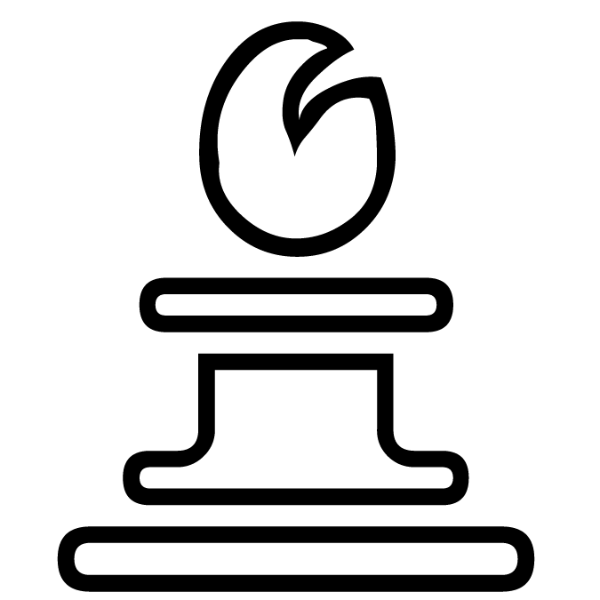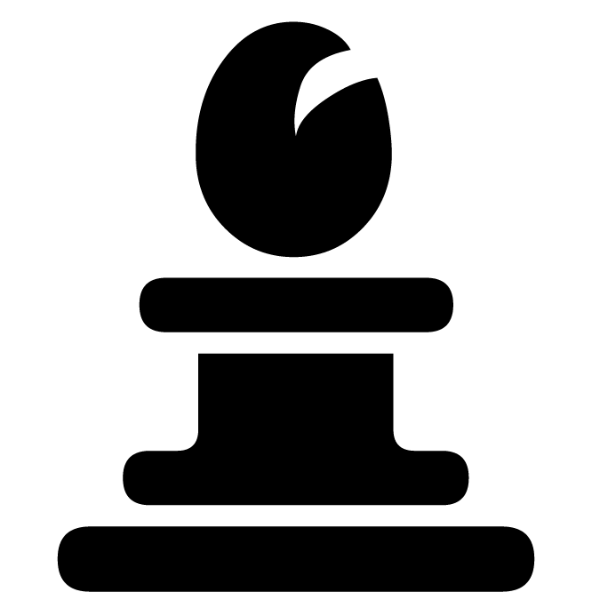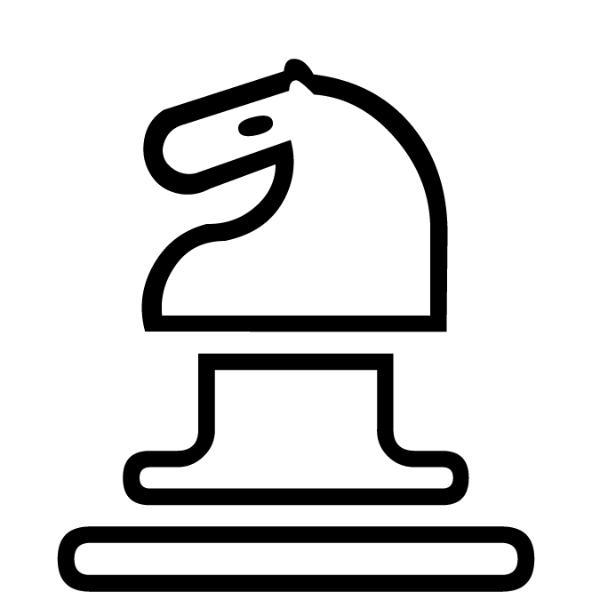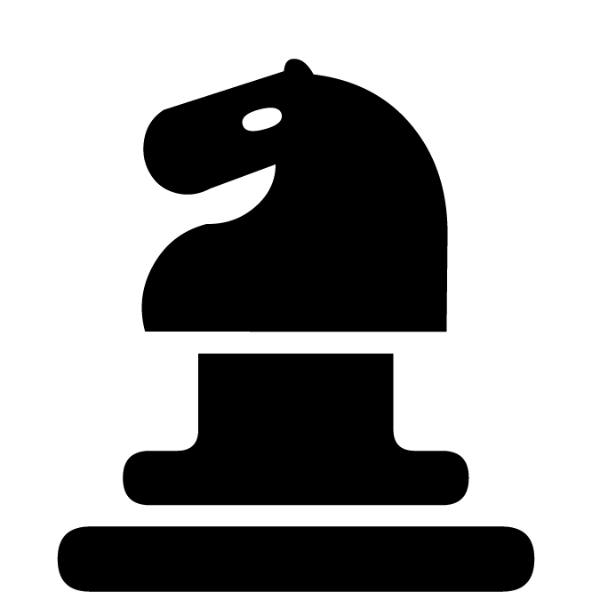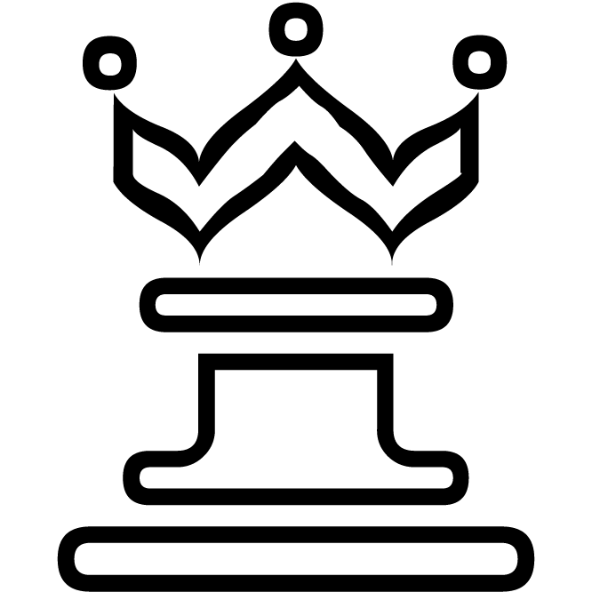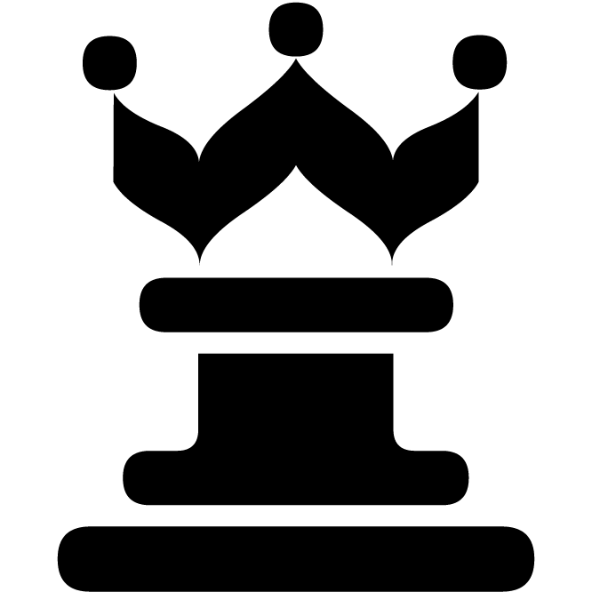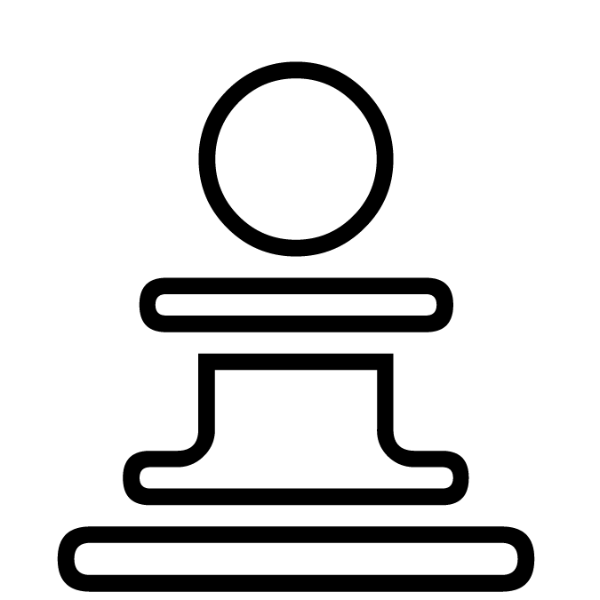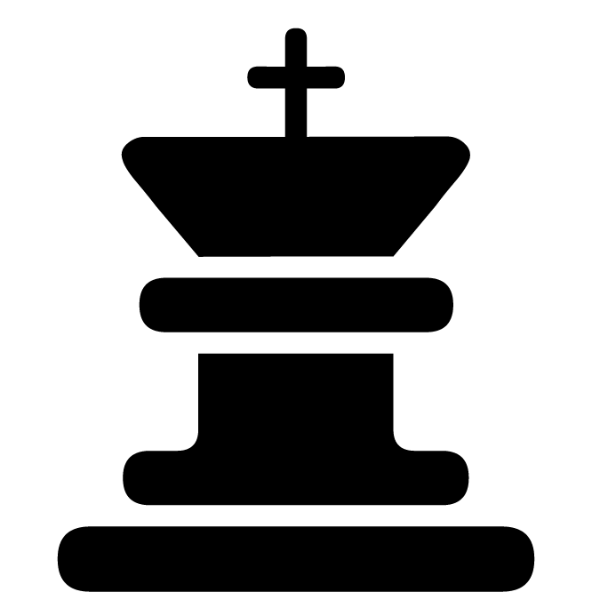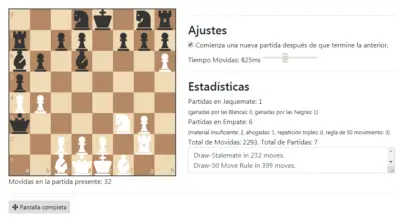
La Fuente Chess Marroquin destaca por su división en segmentos, que otorga un aspecto visual único a cada una de las piezas. Sus secciones superiores estilizadas aportan personalidad y singularidad, haciendo de esta fuente una excelente opción para amantes del ajedrez y proyectos gráficos.
Juego de Ajedrez con la Fuente Marroquin: